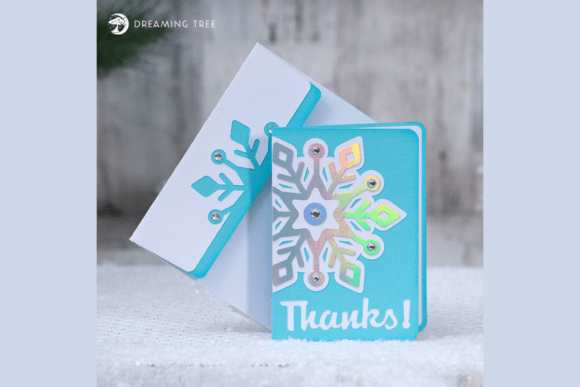
Thank You Card
適切なデザイン要素を見つけるのは難しい場合がありますが、Thank You Cardは作品を即座に引き立てる優れたコレクションを提供します。
POD(オンデマンド印刷)製品、結婚式の招待状、またはソーシャルメディアのグラフィックを作成している場合でも、Thank You Cardは理想的です。